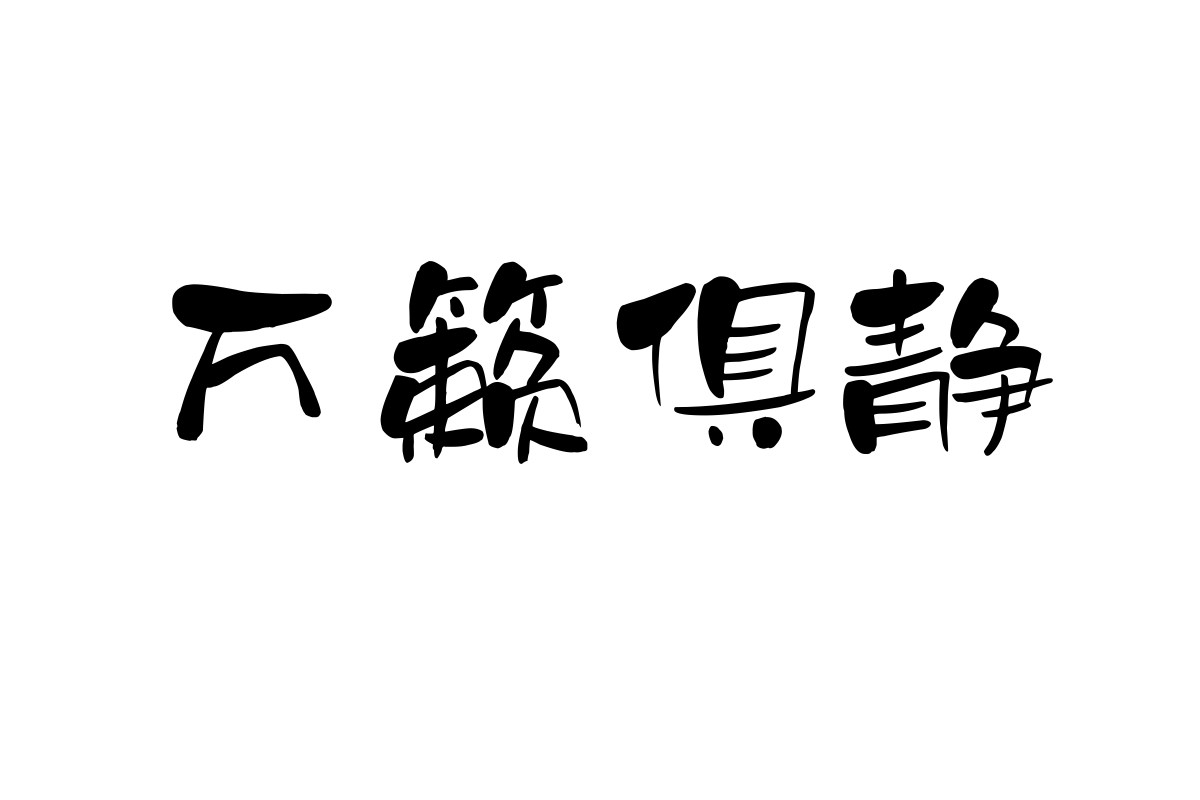
上首大头手写体是一套专为书法设计,特别是用于书写中文汉字的字体。它的特点是笔画粗细不一,给人一种自然、流畅的感觉,适合用于书法创作和日常书写。
特点:
1. 笔画粗细不一,既有粗犷的线条,也有细腻的笔触,使得书写效果更加丰富。
2. 字形结构紧凑,线条流畅,给人一种优雅、自然的感觉。
3. 适用于各种书写场合,如书法、绘画、签名等。